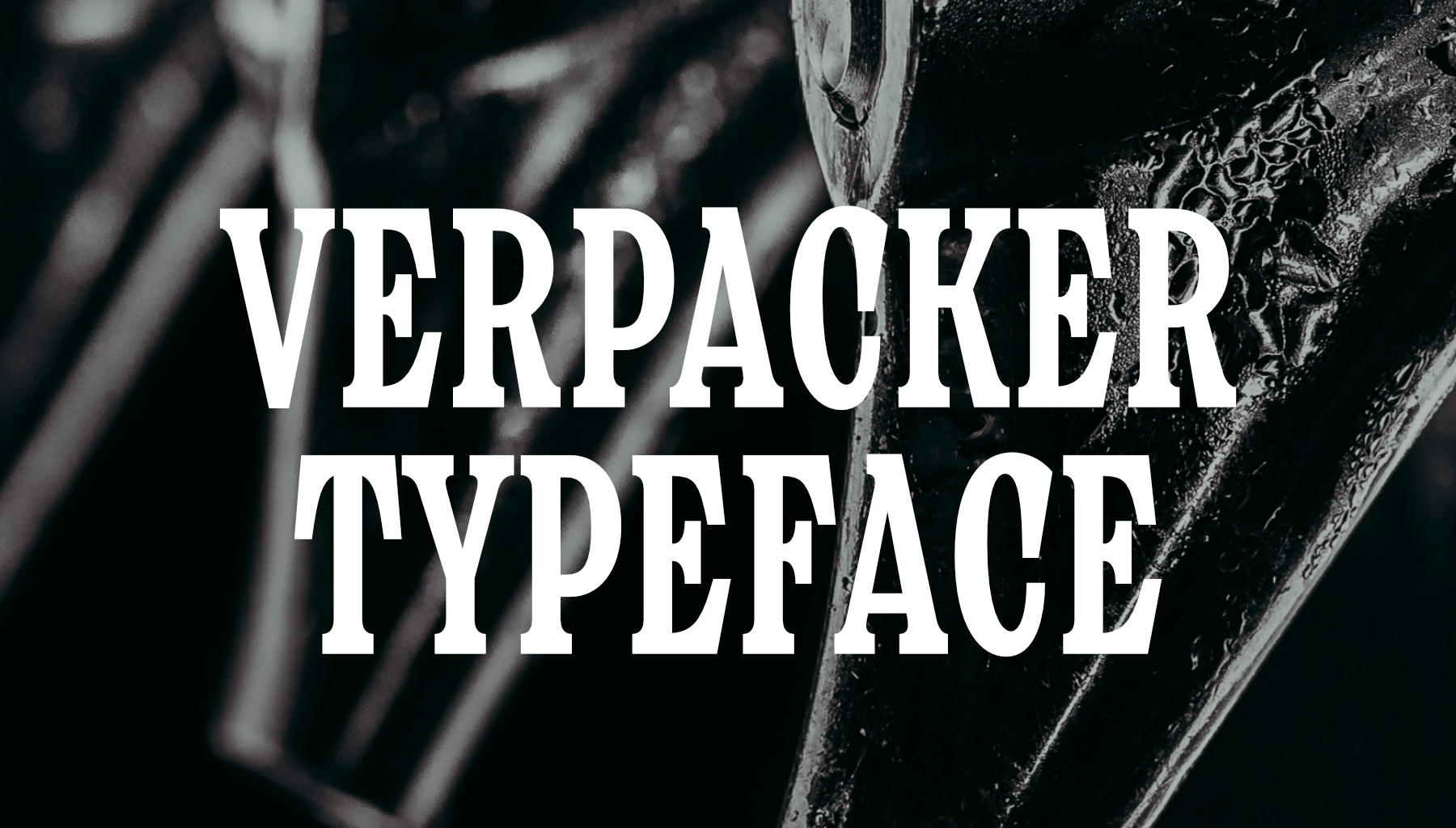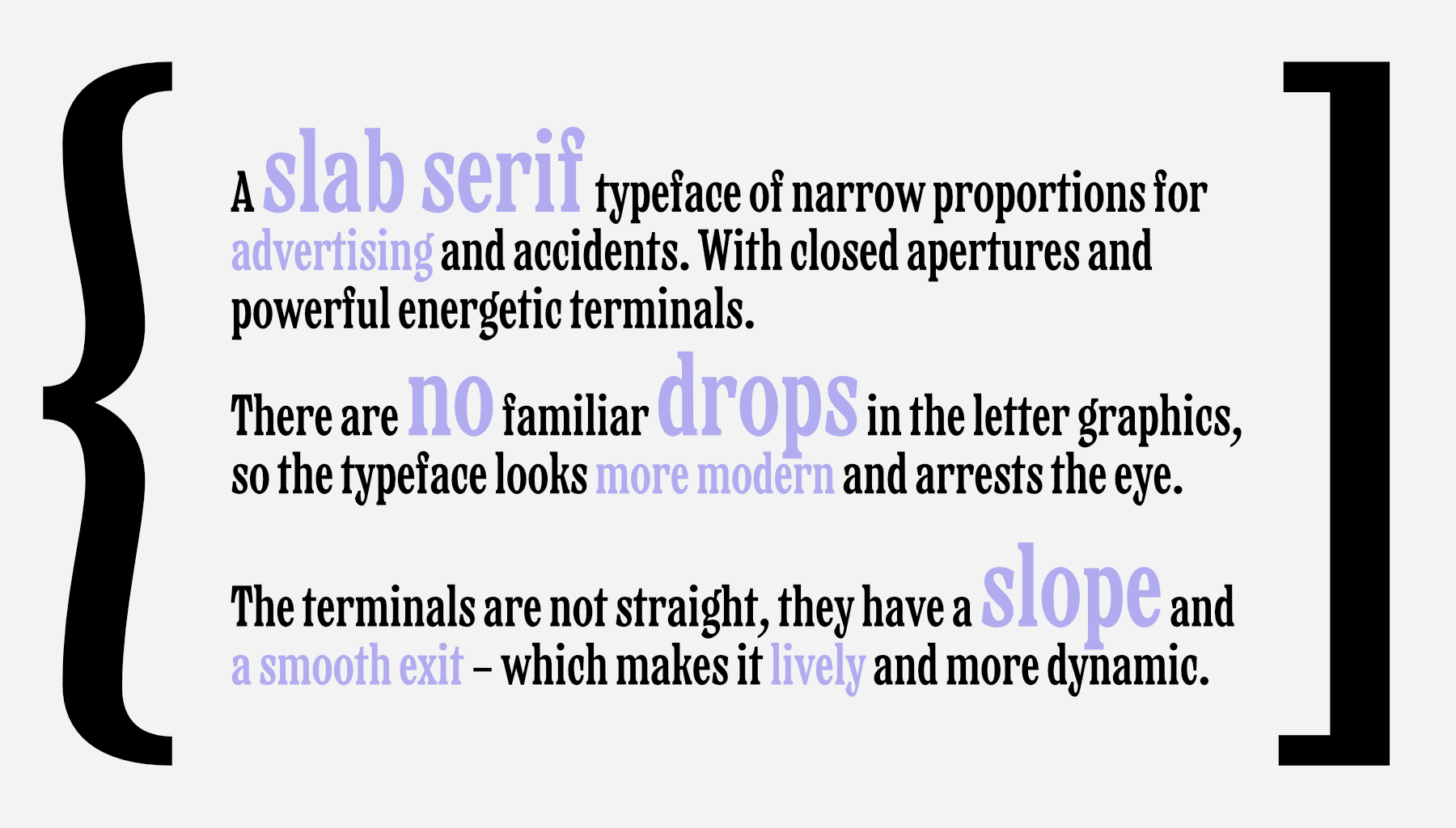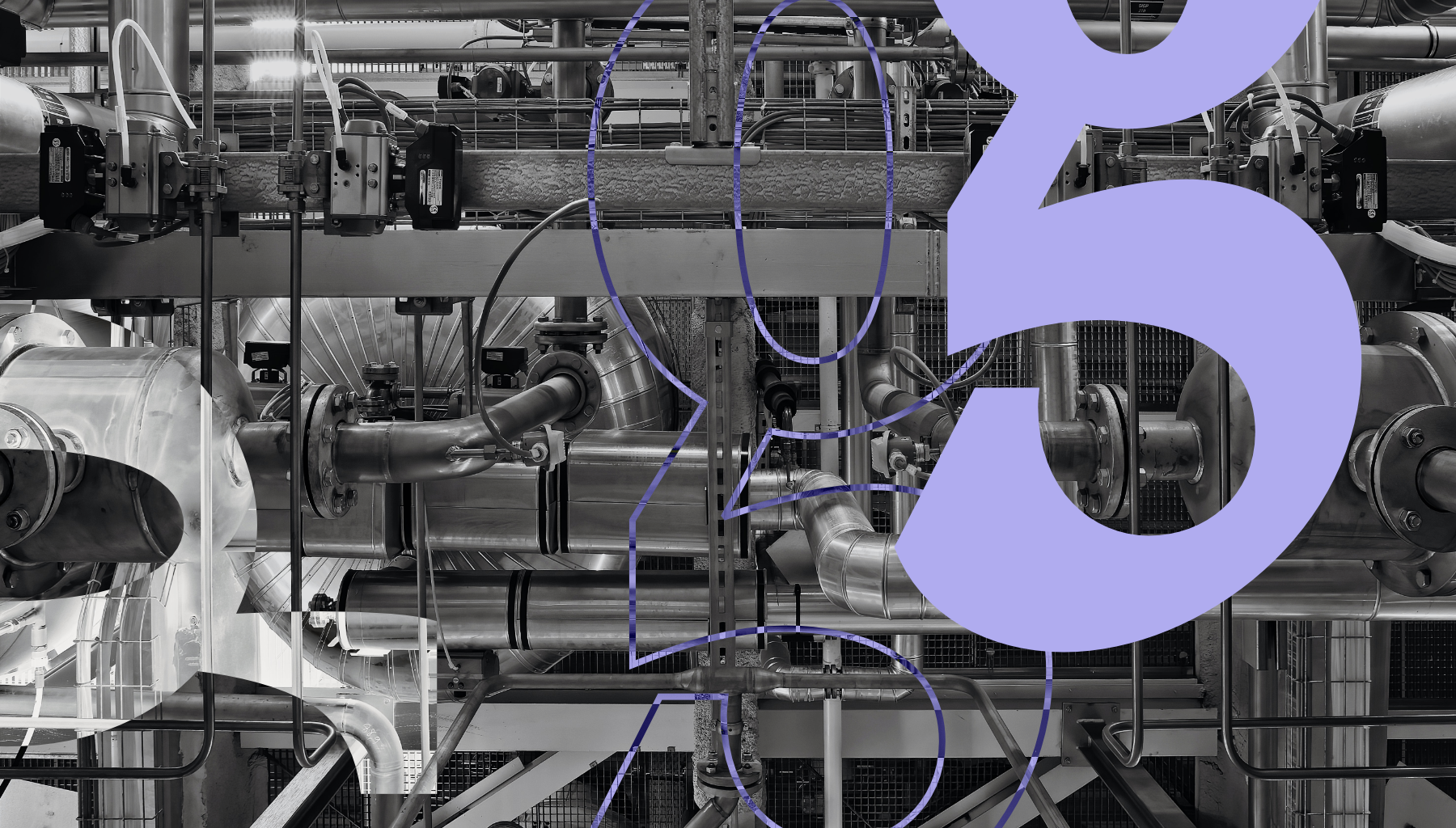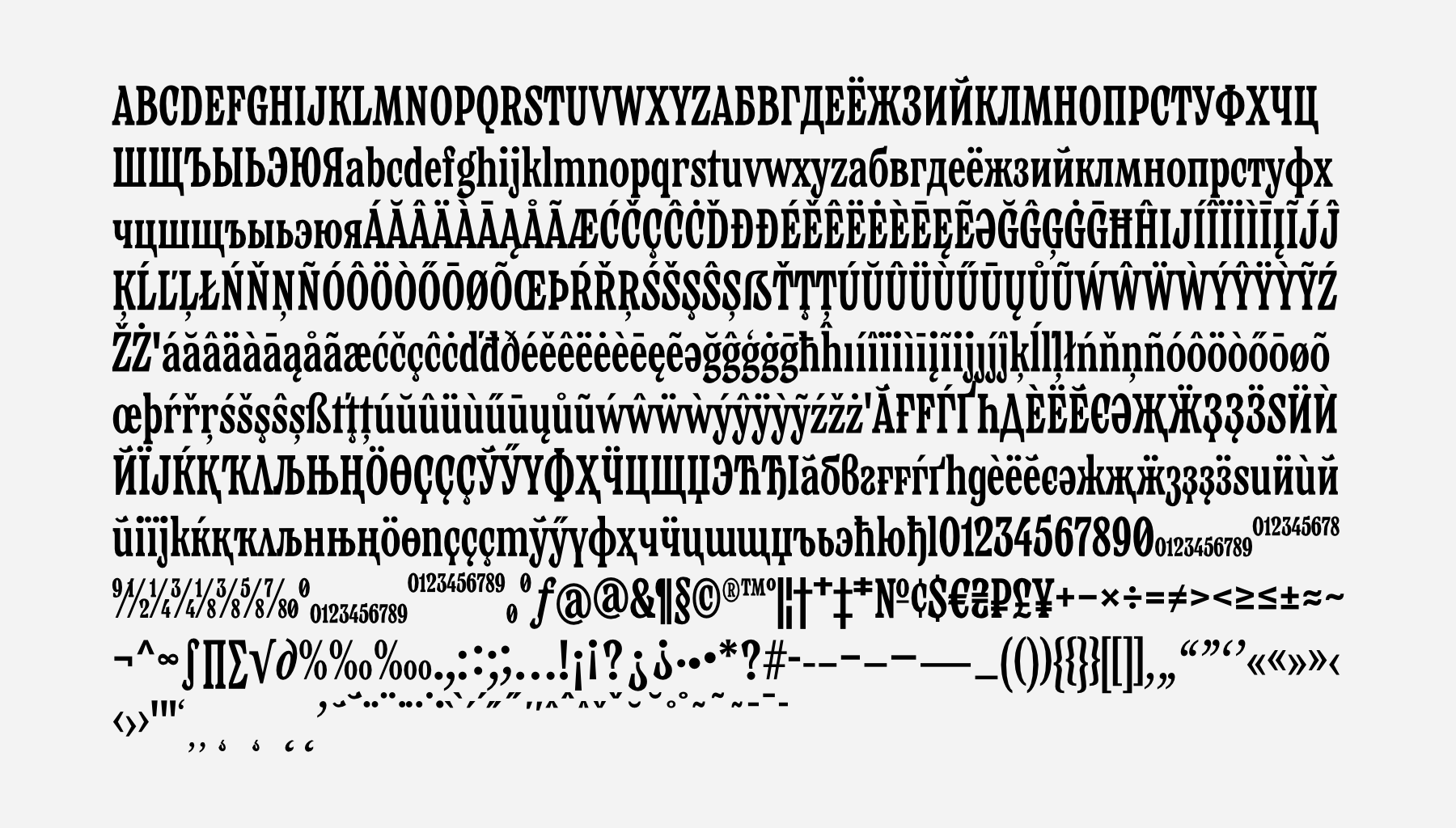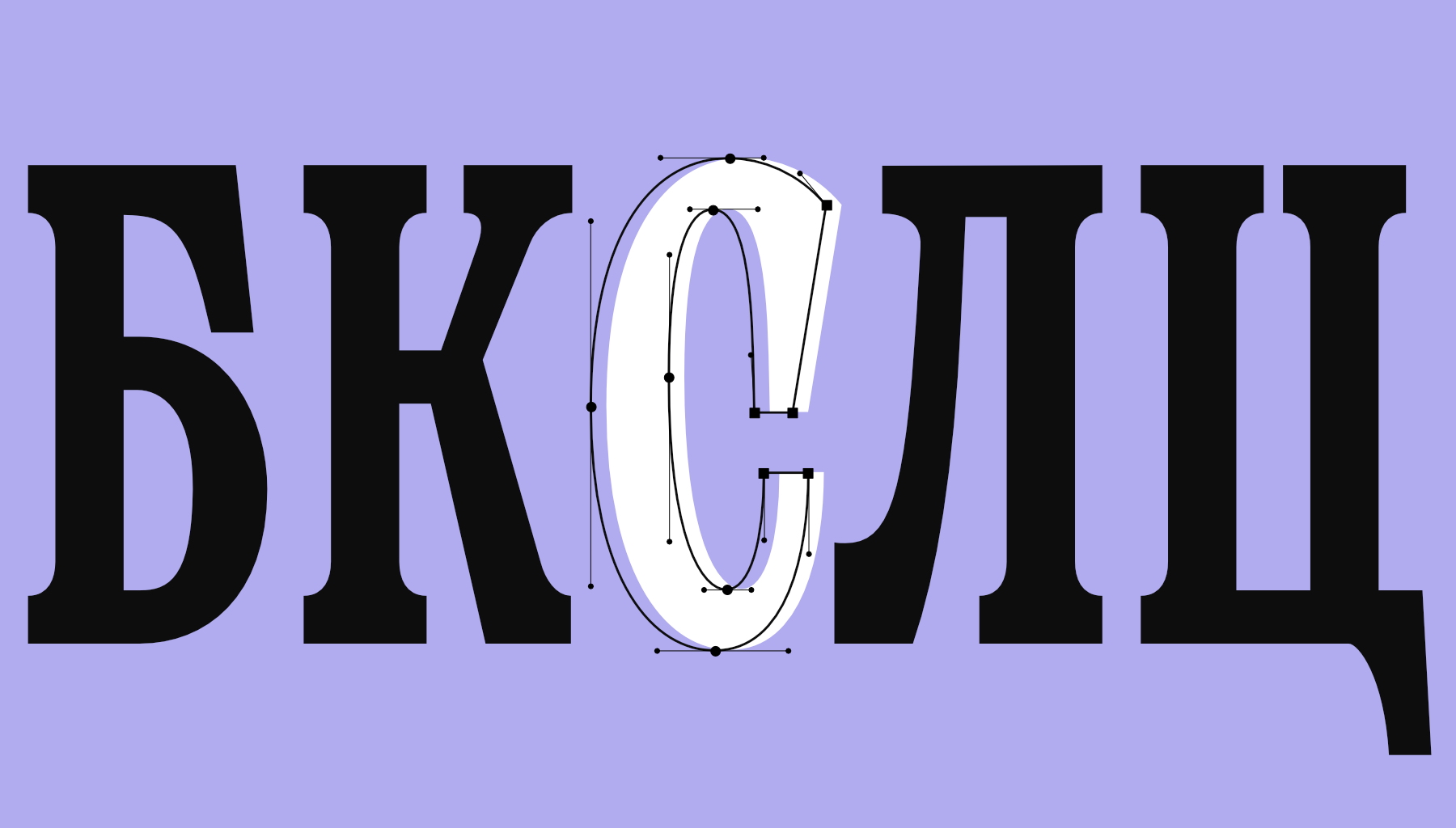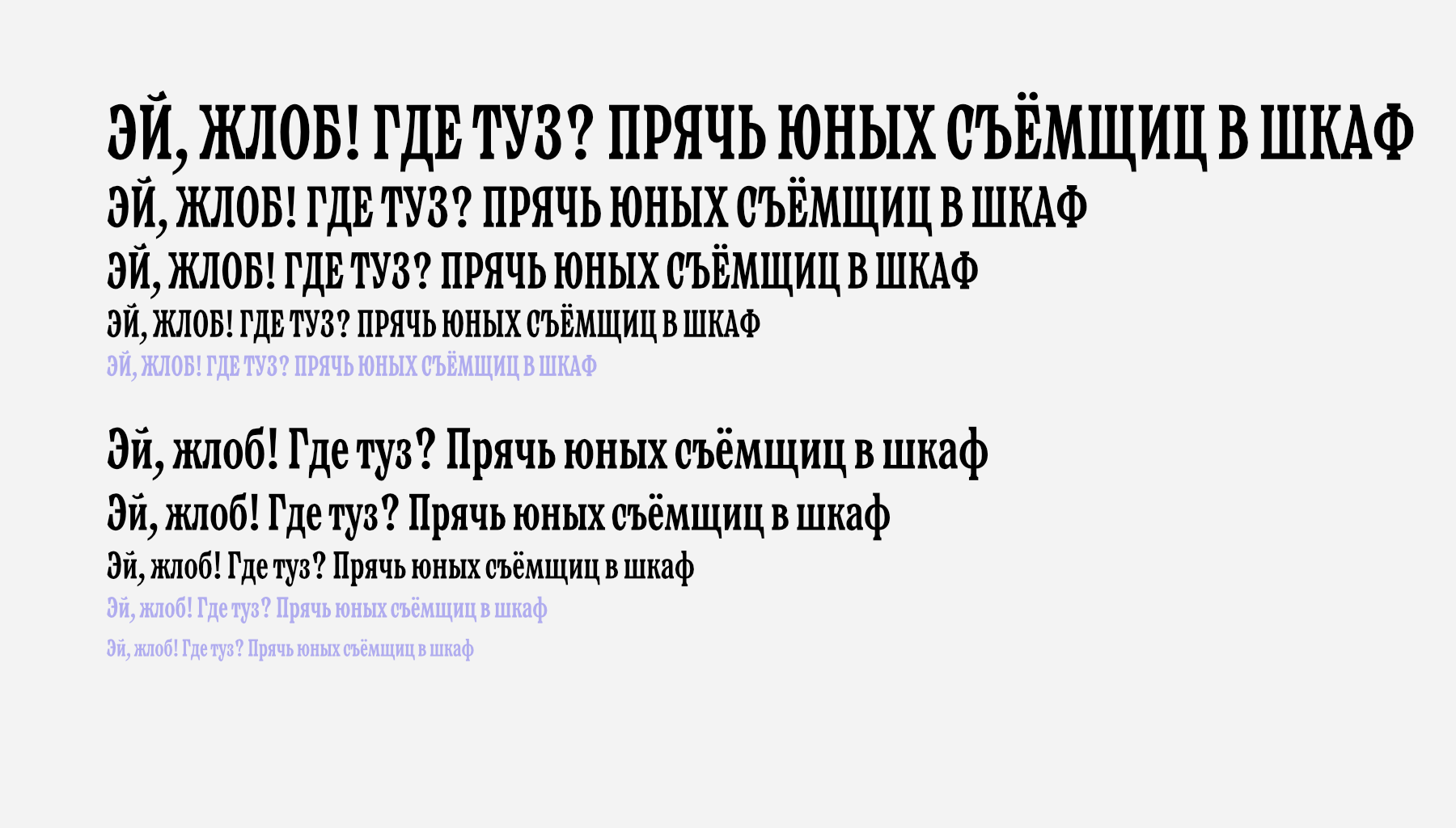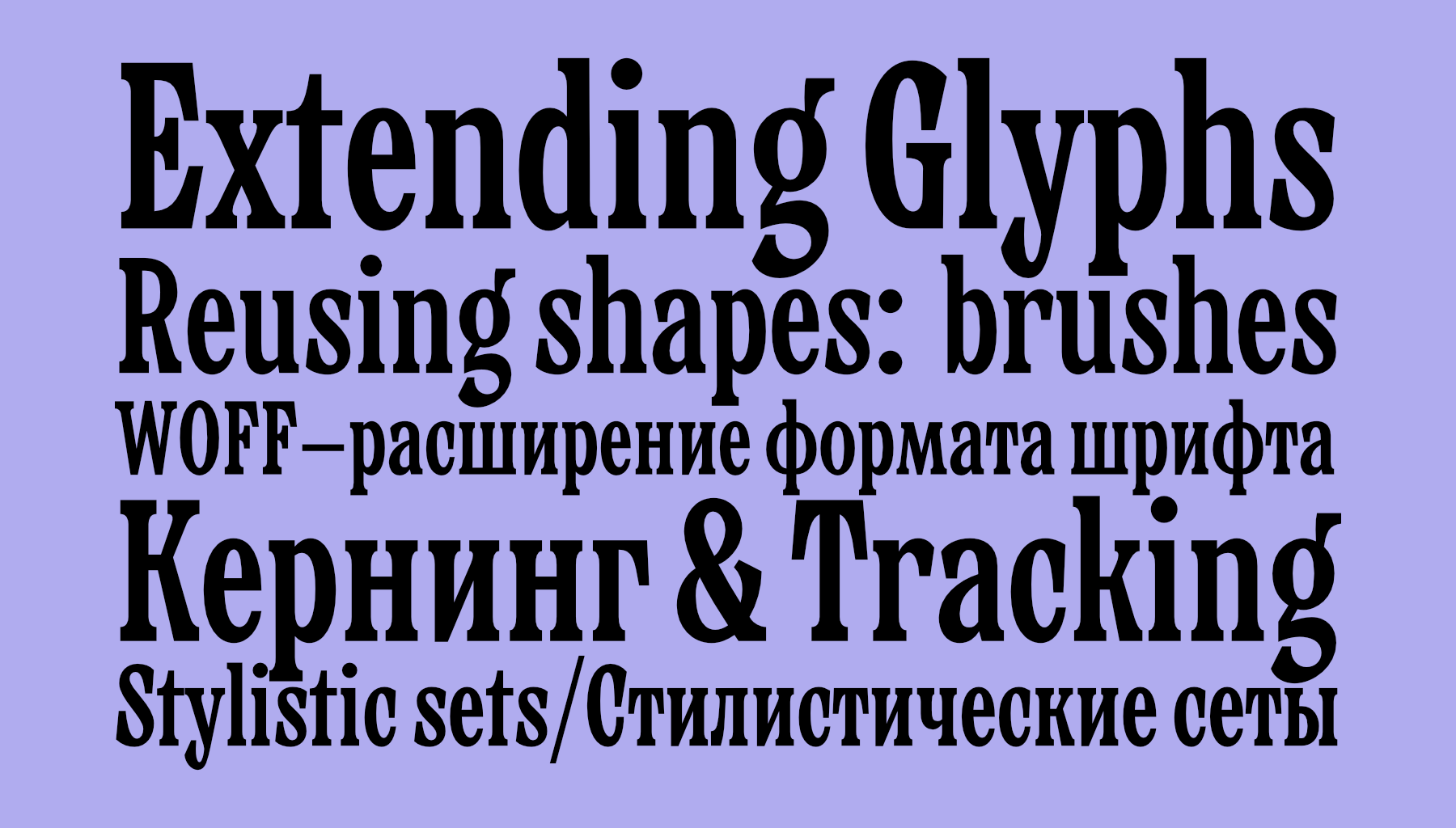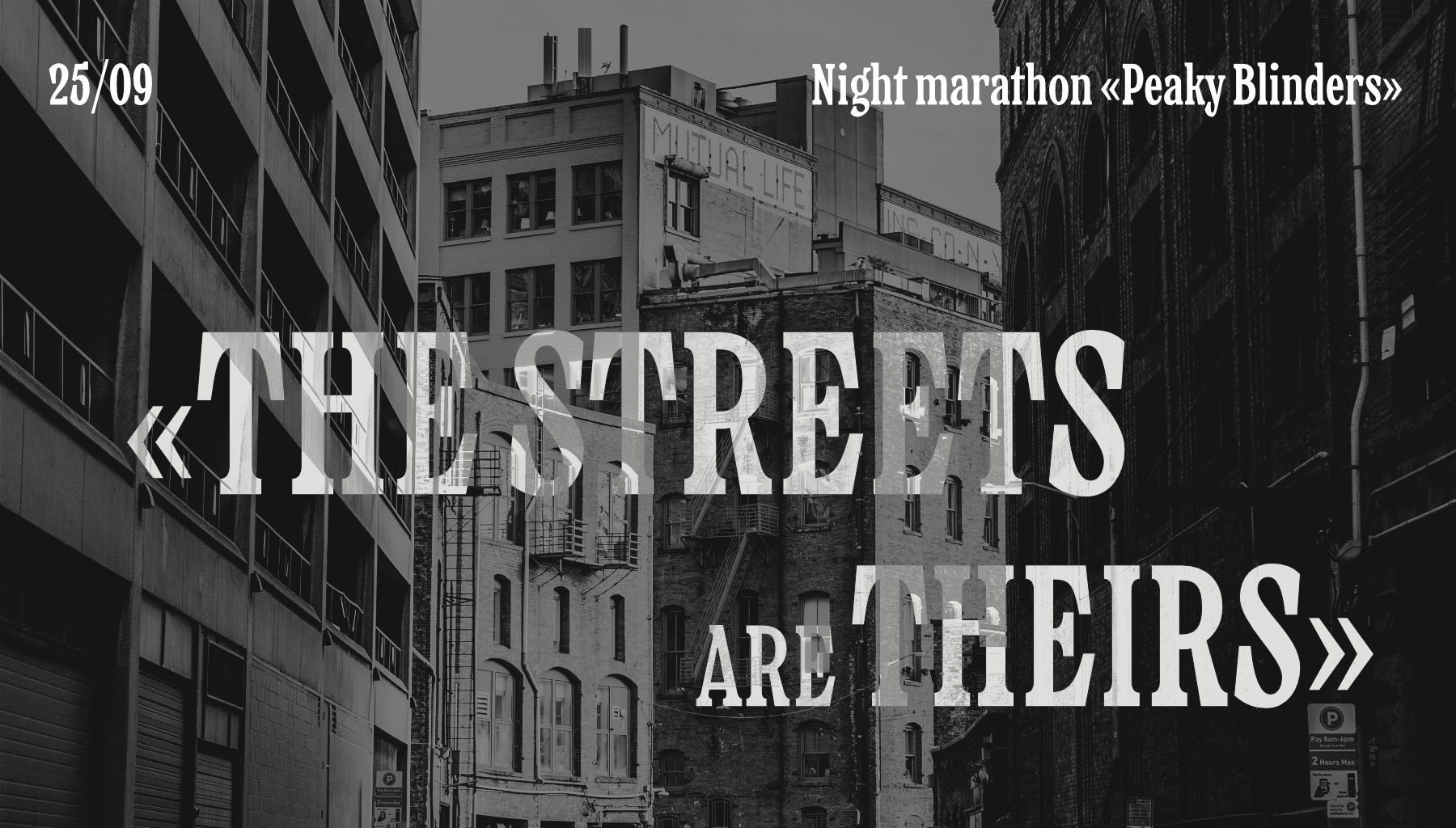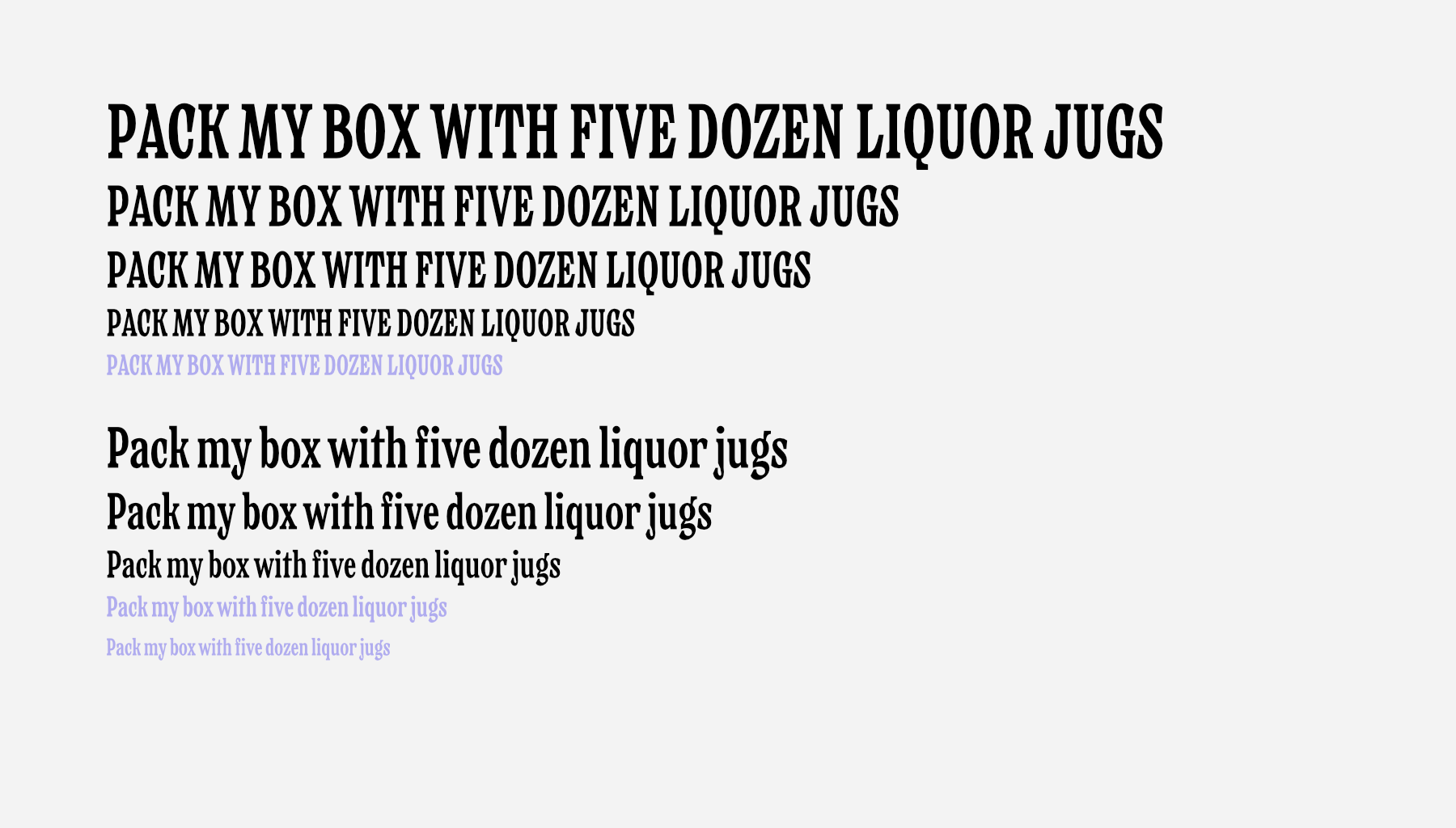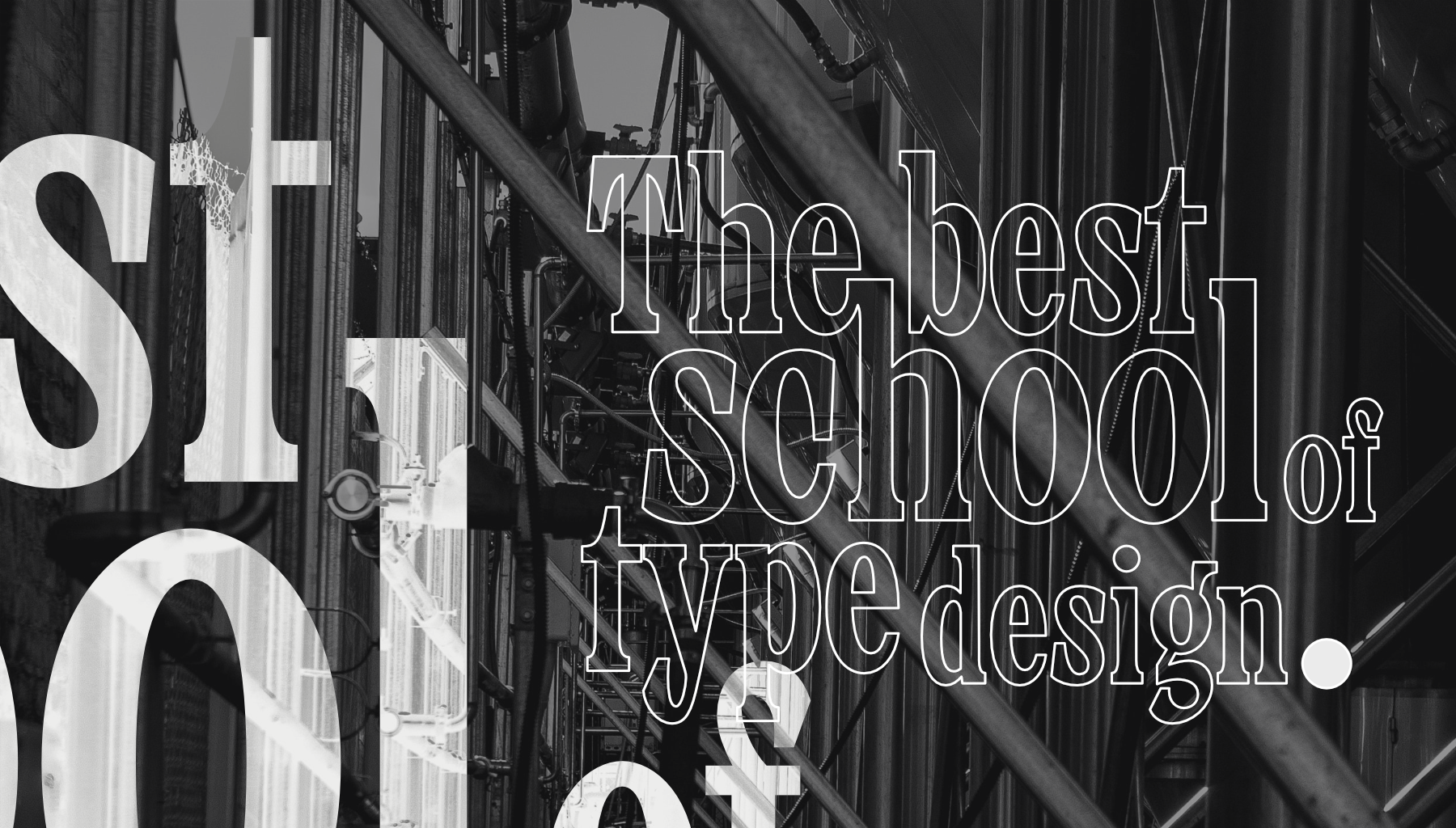
Тиражный шрифт
Verpacker
Verpacker — малоконстраный брусковый шрифт узких пропорций для рекламы и акциденции. C закрытыми апертурами и мощными энергичными терминалами. Шрифт сочетает функциональность и цепляющий характер набора. В графике букв нет привычных капель, так шрифт выглядит современней и задерживает взгляд. Терминалы не прямые, имеют наклон и плавный выход - что делает его живым и более динамичным.
Шрифт малоконстраный, поэтому хорошо читается. Можно использовать в заголовках и коротких текста. А узкие пропорции позволяют использовать где ограничено место, например этикетки и упаковка. Шрифт подойдет производителям товаров FMCG, от напитков, закусок, до молочной и мясной продукции.
Упаковка не единственная возможность для применения. Verpacker подходит для оформления книг, журналов и меню. А также афиш, постеров для выставок, спектаклей и других культурных событий.